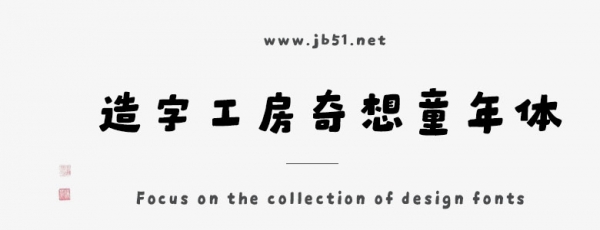
造字工房奇想童年体
造字工房奇想童年体由上首造字字库出品的字体,字体以手账、动漫字体为基础,加之书法体挥毫泼墨的精心绘制。字体既展现了手写字的灵动与自然美感。适合应用于平面宣传设计、网页设计,书法字帖等领域,需要的朋友可以前来本站下载。
字体介绍
造字工房奇想童年体是一款拥有独特艺术风格的手写字体,以手账、动漫字体为基础,加之书法体挥毫泼墨的精心绘制。字体既展现了手写字的灵动与自然美感,也以其精巧的设计给人以视觉上的愉悦和享受,让人能在数字化的时代感受手写字的人情味及魅力。本字体为简体字库,采用OpenType/CID格式,Adobe-GB1-5编码。基于中华人民共和国GB2312-80字符集标准,另按需添加101个汉字。共收容字数6864CJK汉字,ASCII常用字符100个。